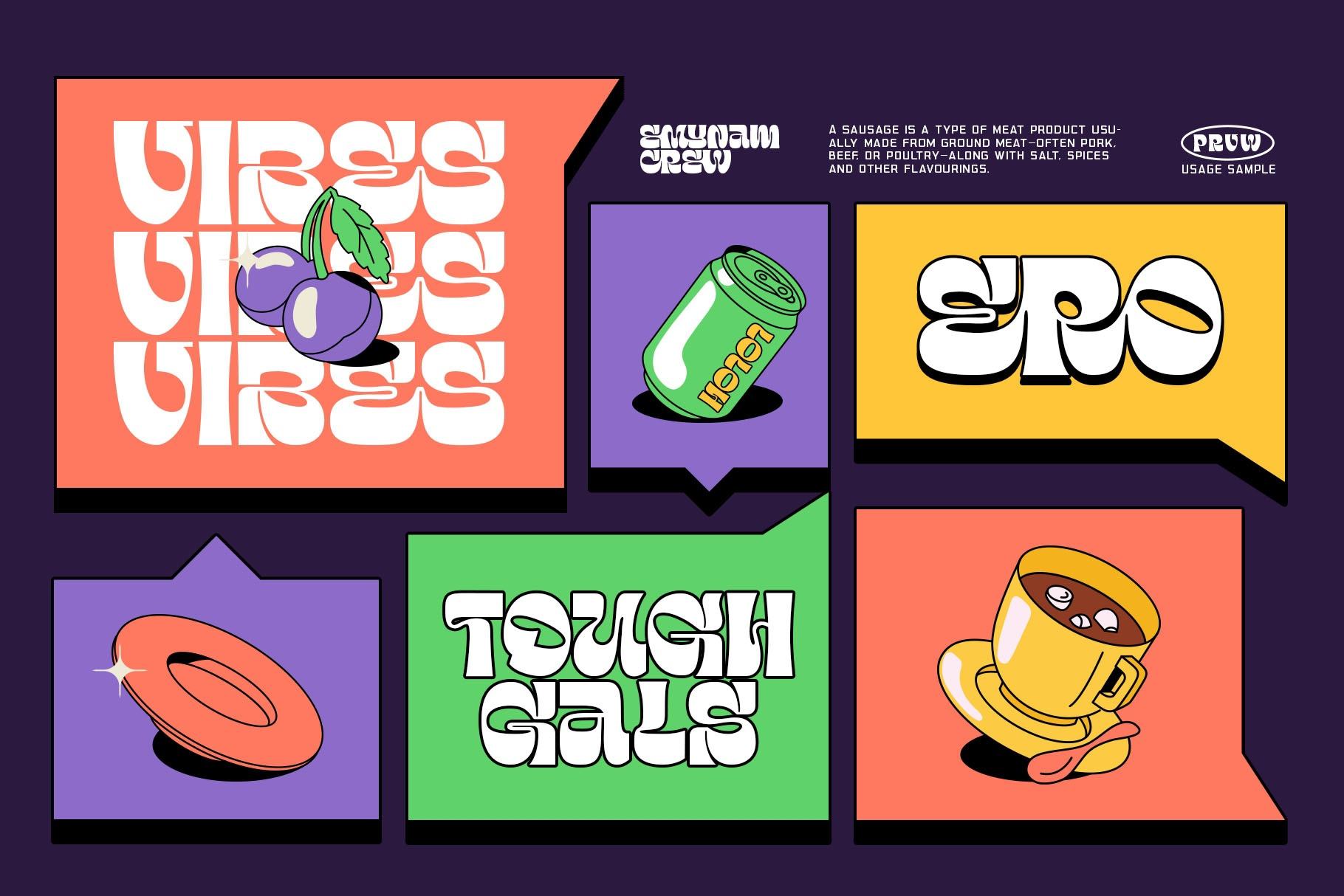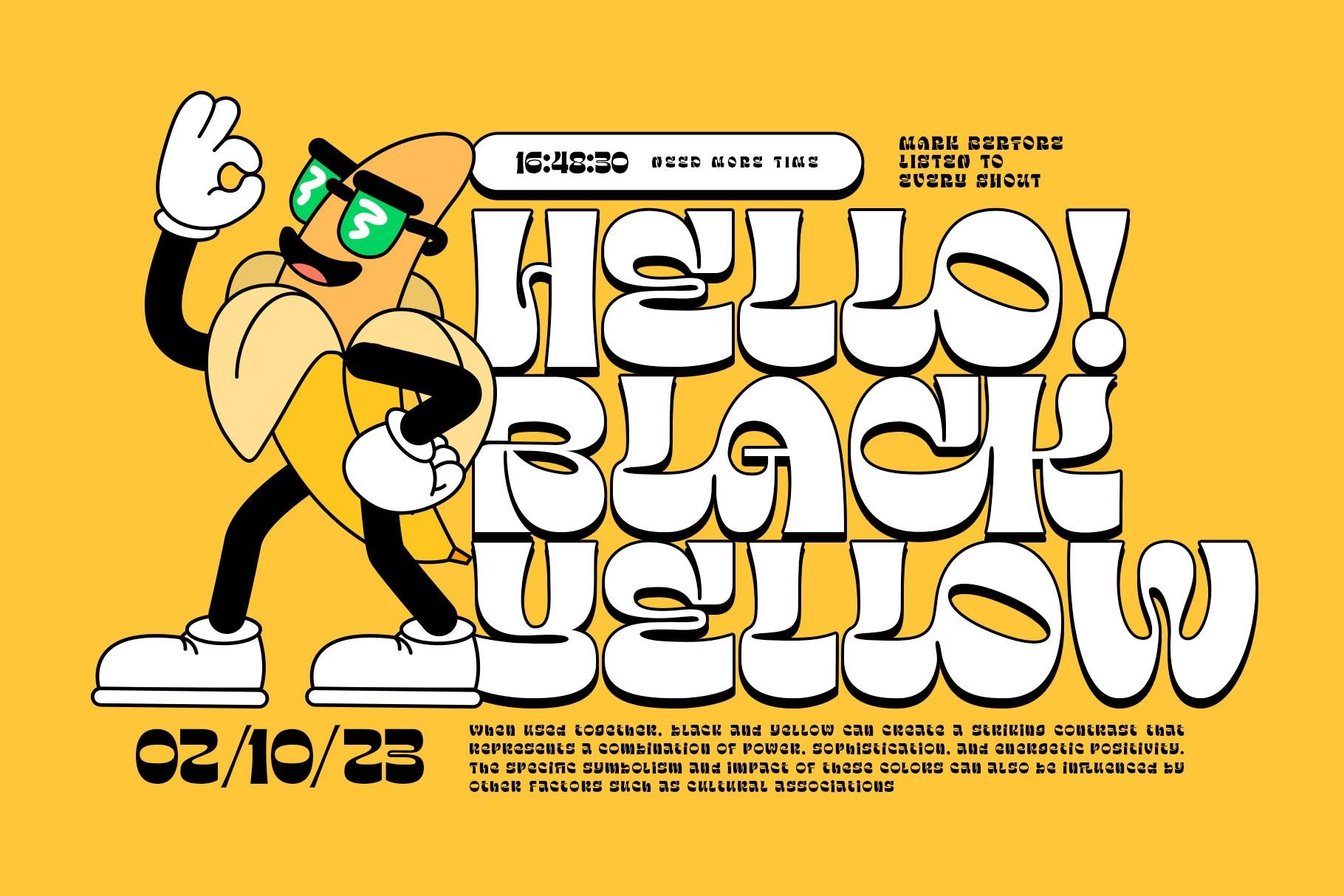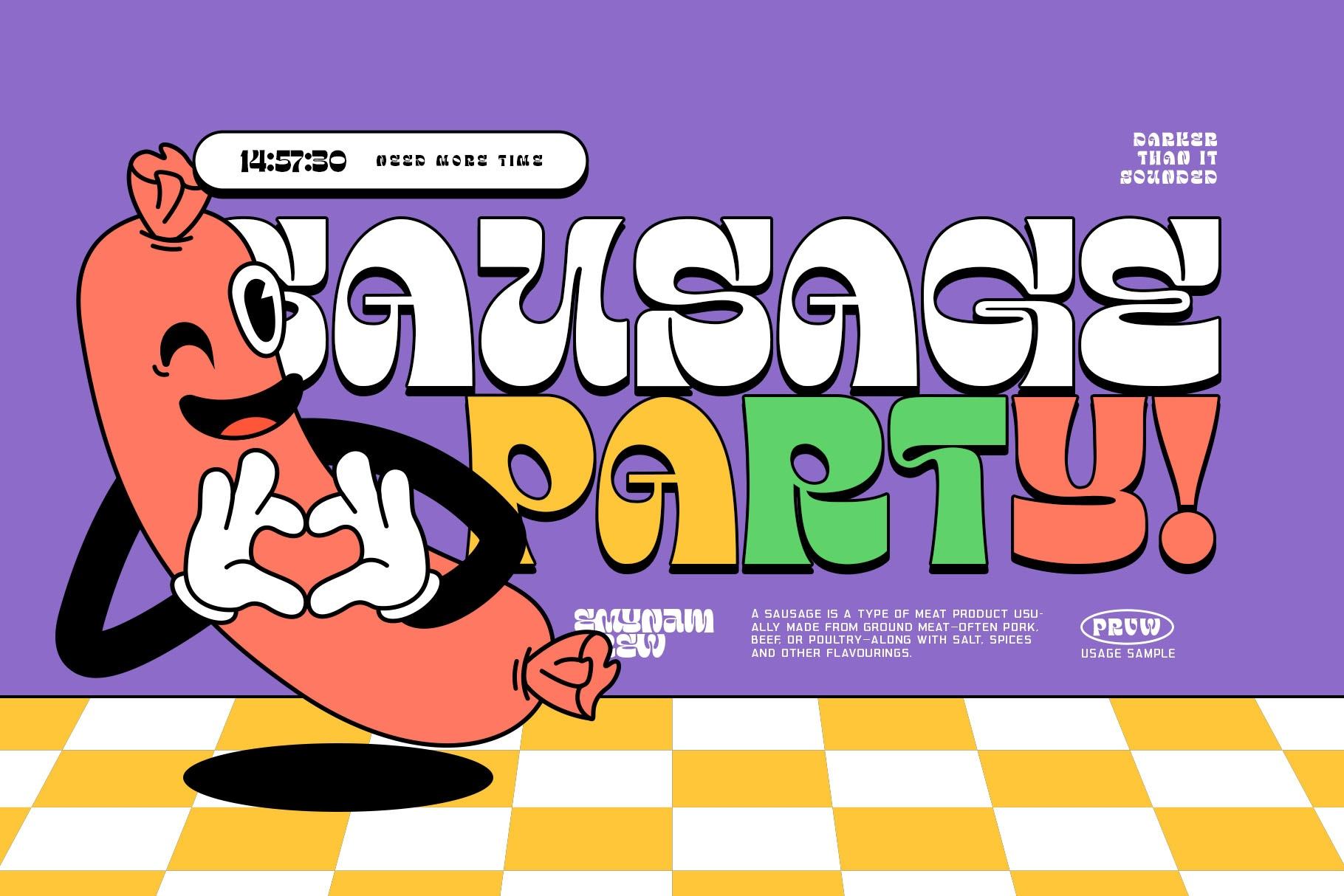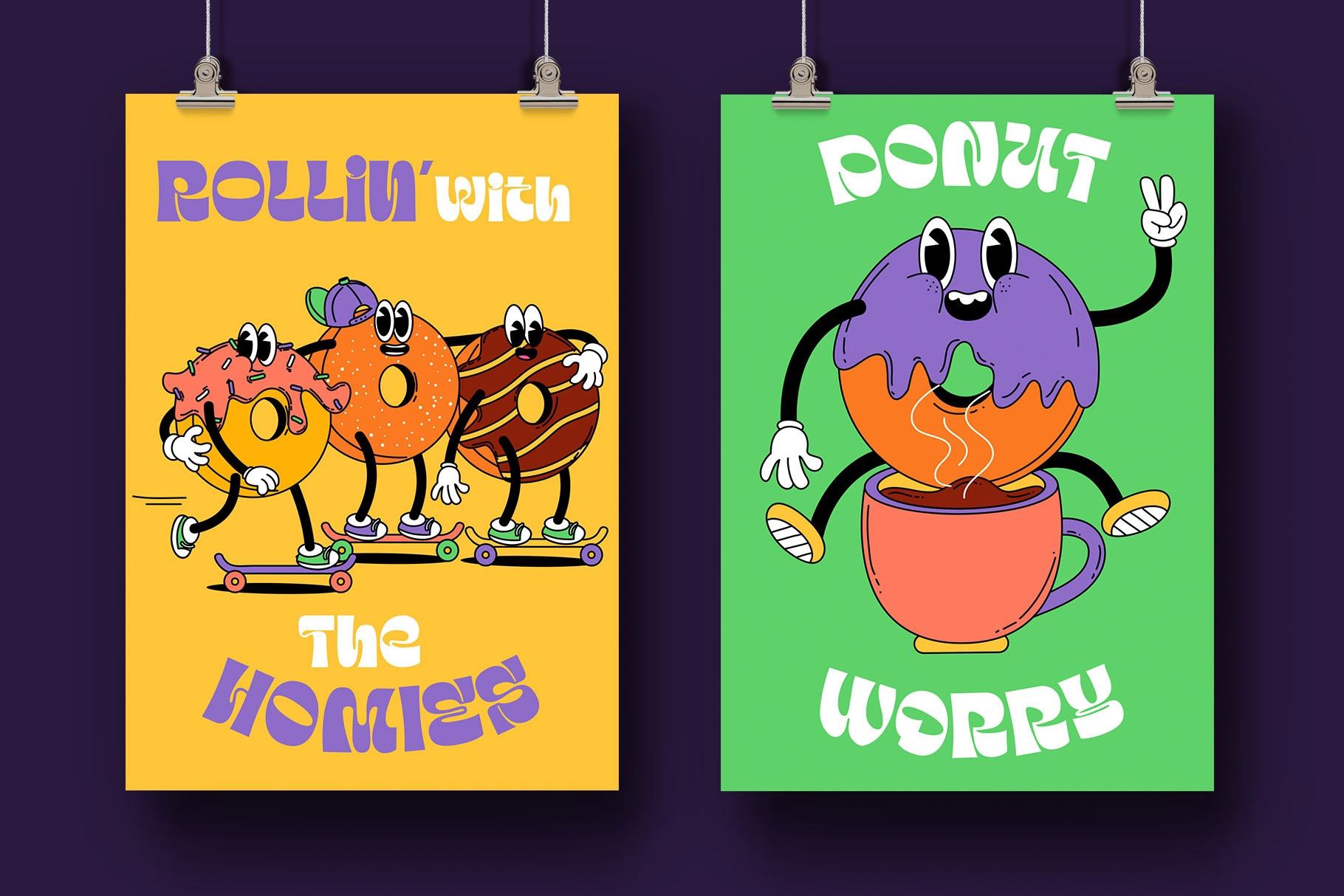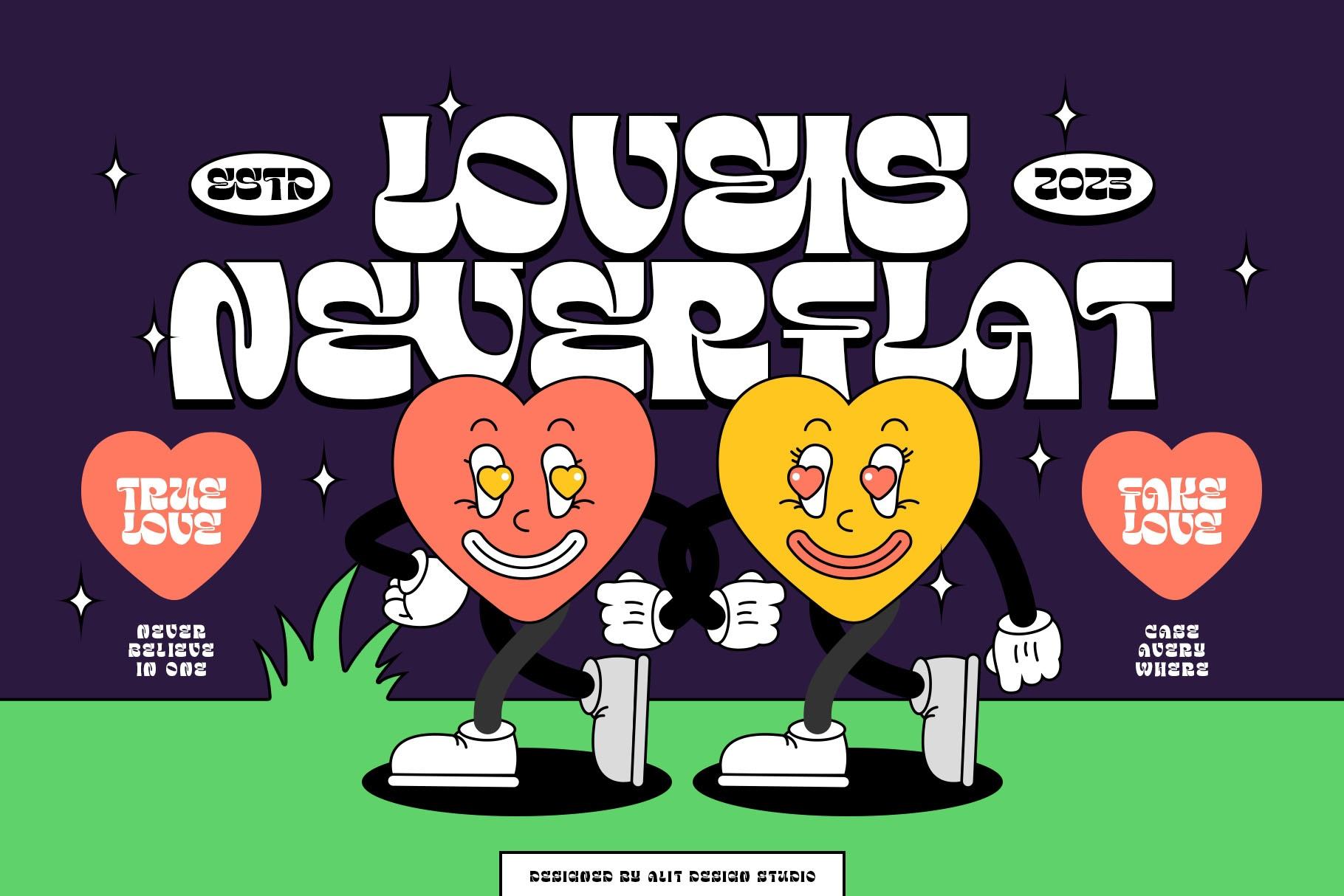
Emynam Crew Font là phông chữ lấy cảm hứng từ cổ điển gợi lên nỗi nhớ những năm 1960 đến 90. Phông chữ mang lại cảm giác hoài cổ vui nhộn của những năm trước với nét hiện đại. Với sự pha trộn độc đáo giữa phong cách, sự tinh tế và 705 glyph khổng lồ, kiểu chữ này là thứ cần phải có đối với bất kỳ ai muốn đưa ra tuyên bố.